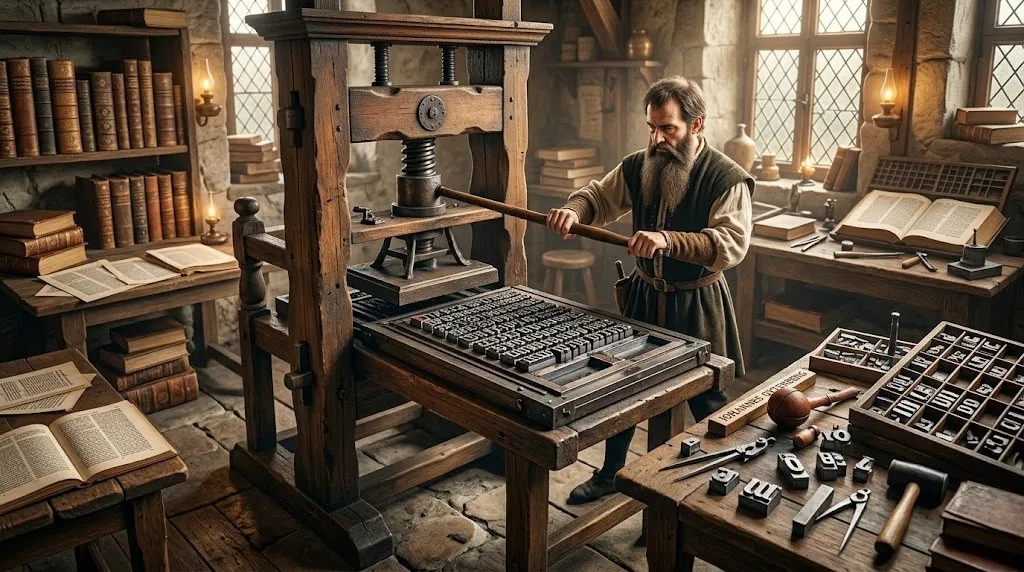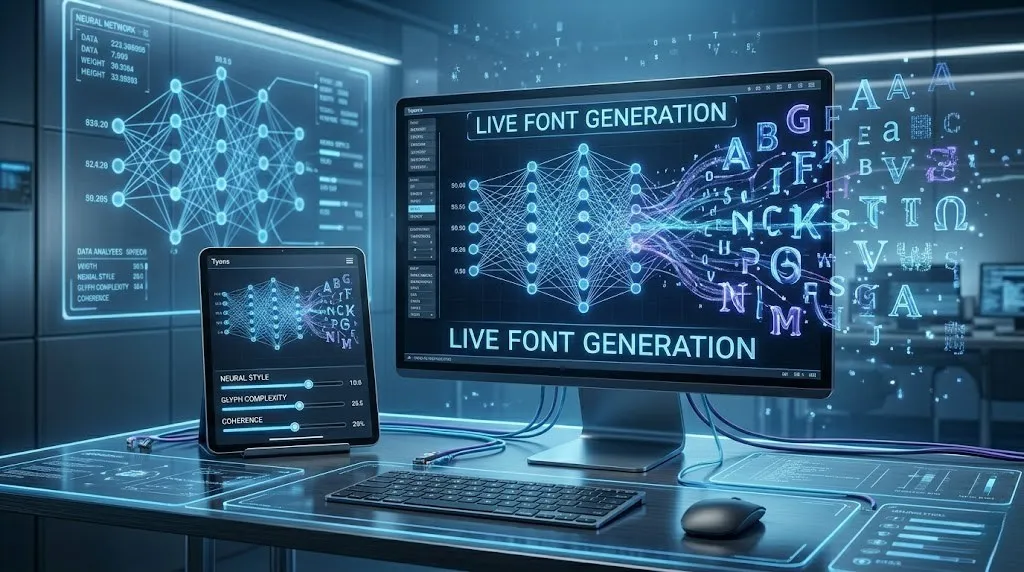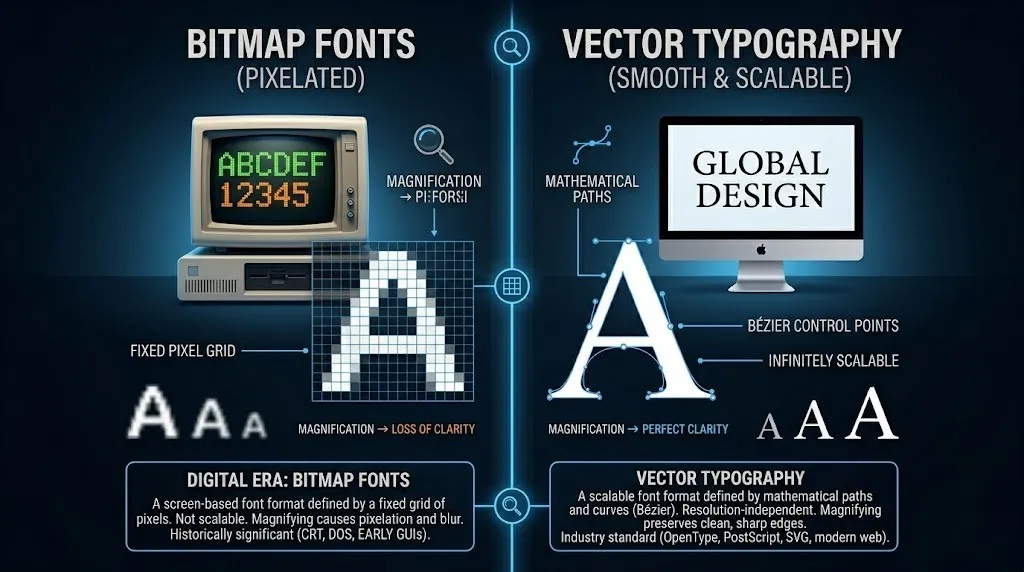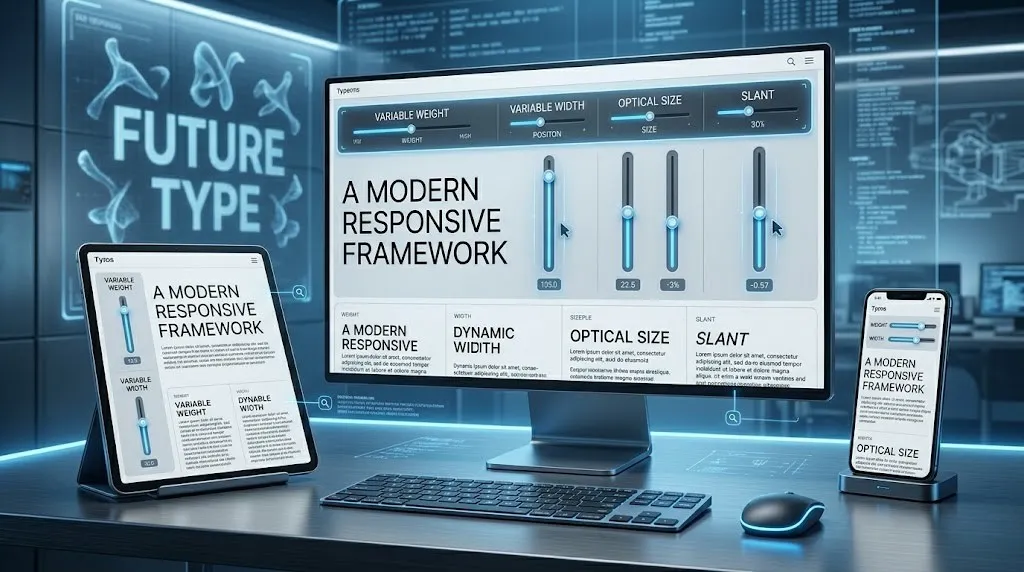
Die Entwicklung digitaler Typografie bis zu KI-Fonts
Viele Designer kämpfen heute mit demselben Problem: Die Auswahl an Schriften ist riesig, die Anforderungen an Typografie wachsen ständig – und trotzdem wirken viele digitale Projekte typografisch austauschbar. Gleichzeitig versprechen KI-Tools eine Revolution, aber kaum jemand weiß genau, was diese Werkzeuge wirklich können und wo ihre Grenzen liegen. Wer Typografie heute sinnvoll einsetzen will, muss verstehen, wo sie herkommt – und wohin sie gerade geht.
Dieser Artikel erzählt genau diese Geschichte: von den ersten gegossenen Bleilettern bis zu Schriften, die sich durch Künstliche Intelligenz in Echtzeit an den Leser anpassen. Schritt für Schritt, ohne Fachchinesisch.
Die physischen Wurzeln: Gutenberg und der Bleisatz
Die physischen Wurzeln Gutenberg und der Bleisatz
Um das Jahr 1450 veränderte Johannes Gutenberg die Welt der Kommunikation von Grund auf. Mit seiner Erfindung des Buchdrucks mit beweglichen Lettern wurde es erstmals möglich, Texte schnell zu vervielfältigen. Die Buchstaben selbst waren physische Objekte – gegossen aus einer Legierung aus Blei, Zinn und Antimon, robust und präzise geformt.
Was heute banal klingt, war damals eine Revolution. Vor Gutenberg mussten Bücher mühsam von Hand abgeschrieben werden. Das kostete Monate, manchmal Jahre. Mit dem Buchdruck dauerte es Tage. Wissen konnte sich verbreiten, Bildung wurde zugänglicher, und die Schrift als visuelles Medium bekam eine völlig neue Bedeutung.
Aber dieser Fortschritt hatte seinen Preis: Schrift blieb physisch gebunden. Wollte man eine andere Schriftart verwenden, musste man neue Lettern gießen lassen. Flexibilität? Kaum vorhanden. Jede Änderung bedeutete Aufwand und Kosten.
Dieser Zustand blieb über Jahrhunderte weitgehend stabil. Das Handwerk verfeinerte sich, die Schriftgestaltung entwickelte sich künstlerisch weiter – aber das Grundprinzip änderte sich nicht. Schrift war Metall, und Metall war Schrift.
Der Fotosatz: Schrift wird leichter
Erst in der Mitte des 20. Jahrhunderts begann der nächste große Umbruch. Der Fotosatz ersetzte das schwere Blei durch Licht. Schriften wurden nicht mehr gegossen, sondern als Negative auf Filmstreifen belichtet. Linsen und Lichtquellen übertrugen die Konturen auf lichtempfindliches Papier oder Film.
Das klingt technisch – aber was es bedeutete, war klar: Schrift wurde leichter, flexibler und günstiger in der Herstellung. Verlage und Druckereien konnten schneller arbeiten. Neue Schriftarten ließen sich einfacher entwickeln und verbreiten.
Gleichzeitig entstanden erste Maschinen, die Text direkt über eine Tastatur setzen konnten. Die IBM Selectric brachte in den 1960er Jahren das Schreibmaschinenkonzept auf ein neues Niveau. Und die Digiset-Maschine von Rudolf Hell war ein frühes Hybrid zwischen Fotosatz und digitaler Steuerung – ein Vorläufer dessen, was bald kommen sollte.
Die Schrift war auf dem Weg ins Digitale. Noch nicht ganz dort, aber die Weichen waren gestellt.
Bitmap-Schriften: Die erste digitale Generation
In den 1960er Jahren erschien die erste wirklich digitale Schrift. Der deutsche Ingenieur Rudolf Hell entwickelte 1968 die Digi Grotesk – eine Schrift, die nicht mehr als physisches Objekt existierte, sondern als Rastergrafik. Buchstaben wurden als Ansammlungen von Pixeln auf einem Bildschirm dargestellt.
Das war ein Durchbruch – aber auch ein Problem. Bitmap-Schriften hatten eine feste Auflösung. Vergrößerte man sie, wurden die einzelnen Pixel sichtbar. Die Buchstaben wirkten treppenförmig, unscharf, unfertig. Für kleine Bildschirme und niedrige Auflösungen funktionierte das. Für hochwertige Druckprodukte oder größere Darstellungen war es eine echte Schwäche.
Trotzdem war der Schritt wegweisend. Er bewies, dass Schrift auf einem Bildschirm existieren konnte – und legte den Grundstein für alles, was danach kam.
Vektorgrafiken: Schrift wird mathematisch
Vektorgrafiken Schrift wird mathematisch
Die Antwort auf das Pixel-Problem kam in den 1980er Jahren. Mit der Einführung von Vektorgrafiken wurde Schrift nicht mehr als Raster aus Pixeln gespeichert, sondern mathematisch beschrieben – als Kurven, Punkte und Linien im Raum.
Adobe brachte 1984 PostScript auf den Markt, eine Seitenbeschreibungssprache, die Schriften und Grafiken mathematisch definierte. Kurz darauf folgten Apple und Microsoft mit TrueType. Beide Ansätze hatten dasselbe Ziel: Schriften stufenlos skalierbar zu machen – ohne Qualitätsverlust, egal ob auf einem kleinen Bildschirm oder einem hochauflösenden Druckbogen.
Das Ergebnis war eine echte Befreiung für die Designbranche. Dieselbe Schriftdatei sah jetzt auf einem kleinen Monitor genauso scharf aus wie auf einem professionellen Laserdrucker. Für Druckereien, Verlage und Agenturen war das eine Erleichterung, die kaum zu überschätzen ist.
Vektorgrafiken sind bis heute das Fundament der digitalen Typografie. Jede Schriftart, die du heute am Bildschirm siehst, basiert auf diesem Prinzip.
Gutenbergs Kernidee war es, Schrift zugänglich zu machen. Das gilt heute mehr denn je – in einer Welt, in der Schrift nicht nur auf Papier erscheint, sondern auf Bildschirmen jeder Größe, in Apps, auf Werbeflächen, in E-Books und bald auf noch mehr Oberflächen des Alltags.
Künstliche Intelligenz ist das nächste Kapitel dieser langen Geschichte. Und wer dieses Kapitel versteht, kann es aktiv mitgestalten – statt nur zuzuschauen. Wie man mit verzerrtem Text auf TikTok auffällt, zeigt unser Glitch-Text-Guide.